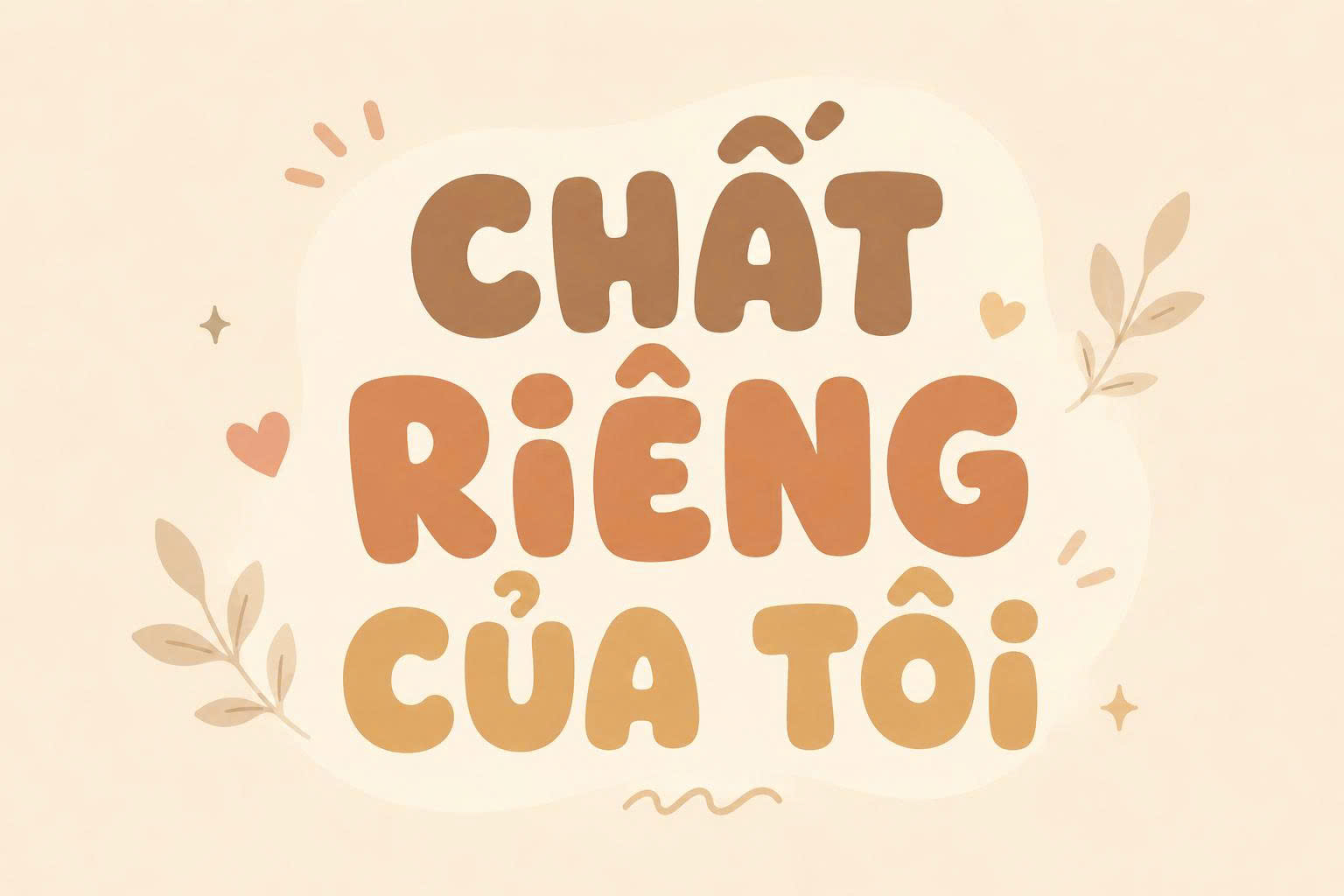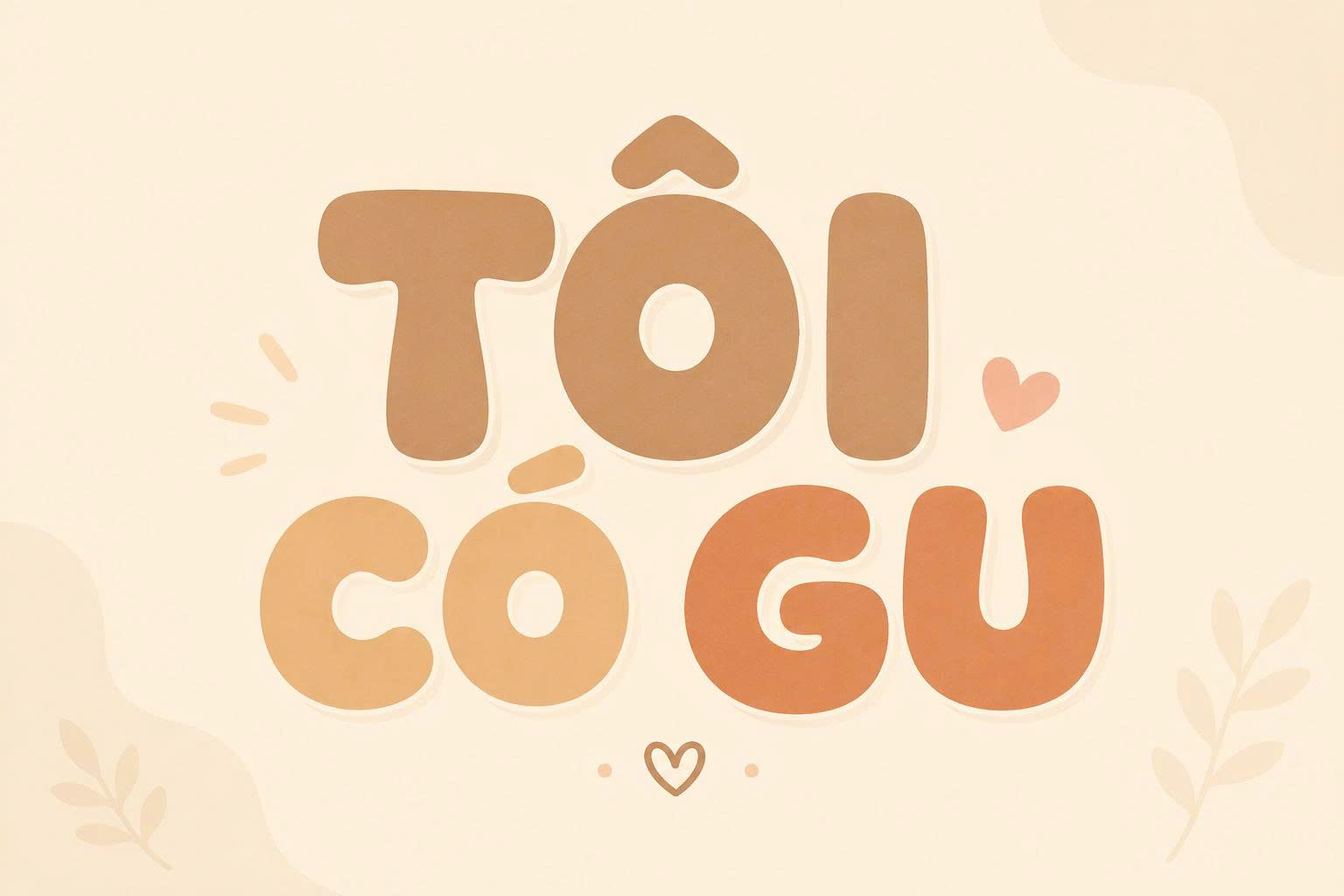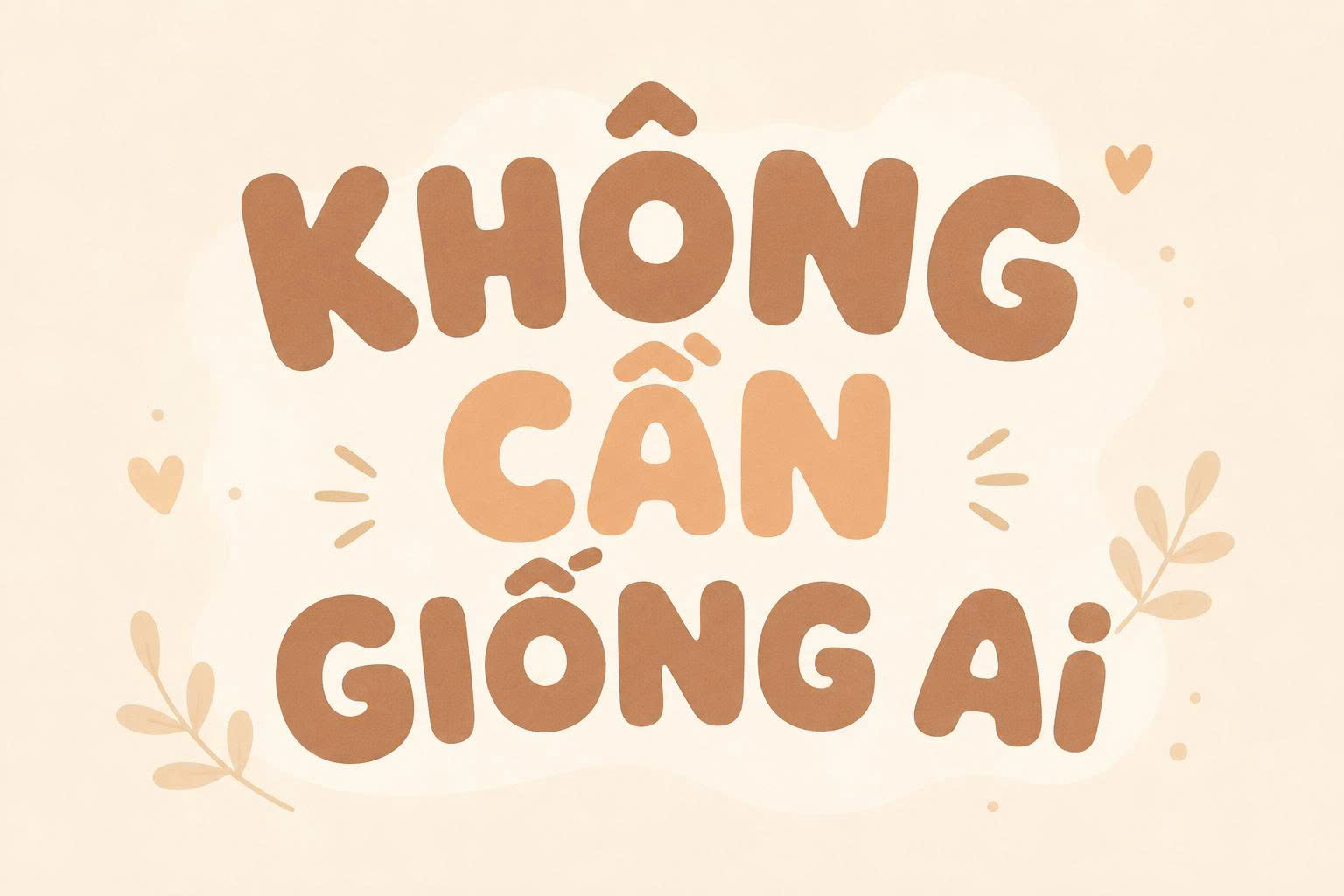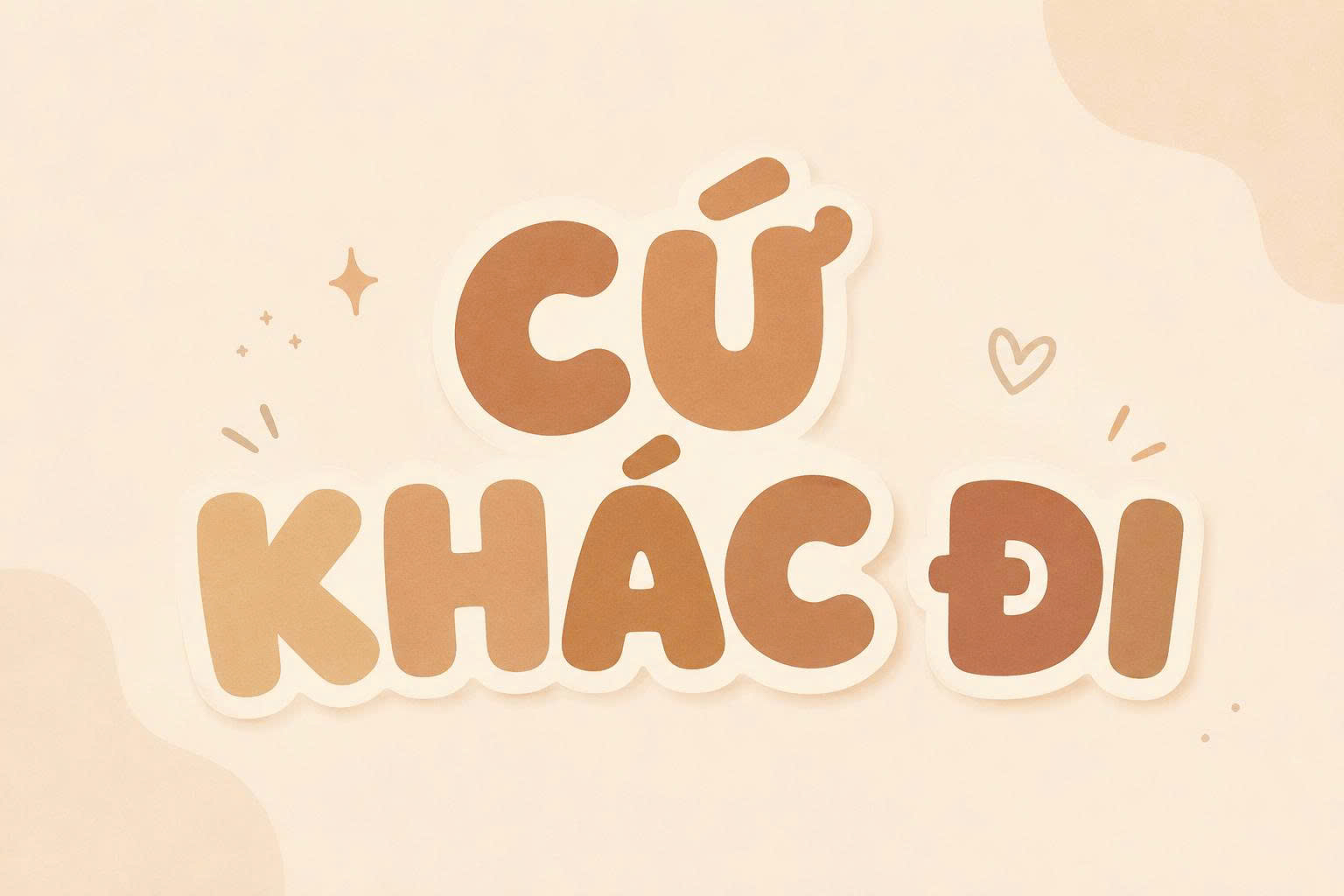
Font UTM Cookies Việt hóa là bộ phông chữ viết tay (Handwritten) mang phong cách ngọt ngào, mập mạp và vô cùng đáng yêu. Nằm trong hệ sinh thái font UTM kinh điển, bộ chữ này mô phỏng nét vẽ tay tự nhiên với các đường nét bo tròn thân thiện, mang lại cảm giác ấm áp và gần gũi cho mọi bản thiết kế. Doozypack.vn cung cấp link download font UTM Cookies chuẩn, hỗ trợ đầy đủ tiếng Việt không lỗi dấu thanh để bạn tự do sáng tạo bao bì bánh kẹo, thiệp mời hay nhãn dán sản phẩm handmade.
Đặc điểm thẩm mỹ của bộ phông chữ UTM Cookies Việt hóa
UTM Cookies không chỉ đơn thuần là một kiểu chữ dễ thương; nó sở hữu cấu trúc hình học thông minh giúp duy trì sự cân bằng giữa tính nghệ thuật và độ dễ đọc.
Phong cách viết tay mập mạp và “ngon mắt”
Đặc trưng lớn nhất của font UTM Cookies là độ dày nét chữ đồng nhất với các góc được bo tròn mềm mại. Các ký tự gợi nhớ đến hình dáng của những chiếc bánh quy vừa ra lò hoặc những nét vẽ bằng bút dạ đậm màu. Chính sự mập mạp này tạo ra một hiệu ứng thị giác “ngon mắt”, rất phù hợp để kích thích vị giác của khách hàng trong các ngành hàng thực phẩm và đồ ngọt.
Hệ thống dấu tiếng Việt chuẩn hóa 100%
Nỗi đau lớn nhất của designer khi tìm phông chữ viết tay là lỗi nhảy font ở các ký tự đặc thù như ơ, ư, đ. Phiên bản utm cookies Việt hóa tại Doozypack.vn đã xử lý triệt để vấn đề này. Các bộ dấu thanh (sắc, huyền, hỏi, ngã, nặng) được tinh chỉnh mập mạp hài hòa với thân chữ gốc, đảm bảo văn bản luôn chỉn chu và đạt độ thẩm mỹ cao nhất trên các ấn phẩm in ấn chuyên nghiệp.